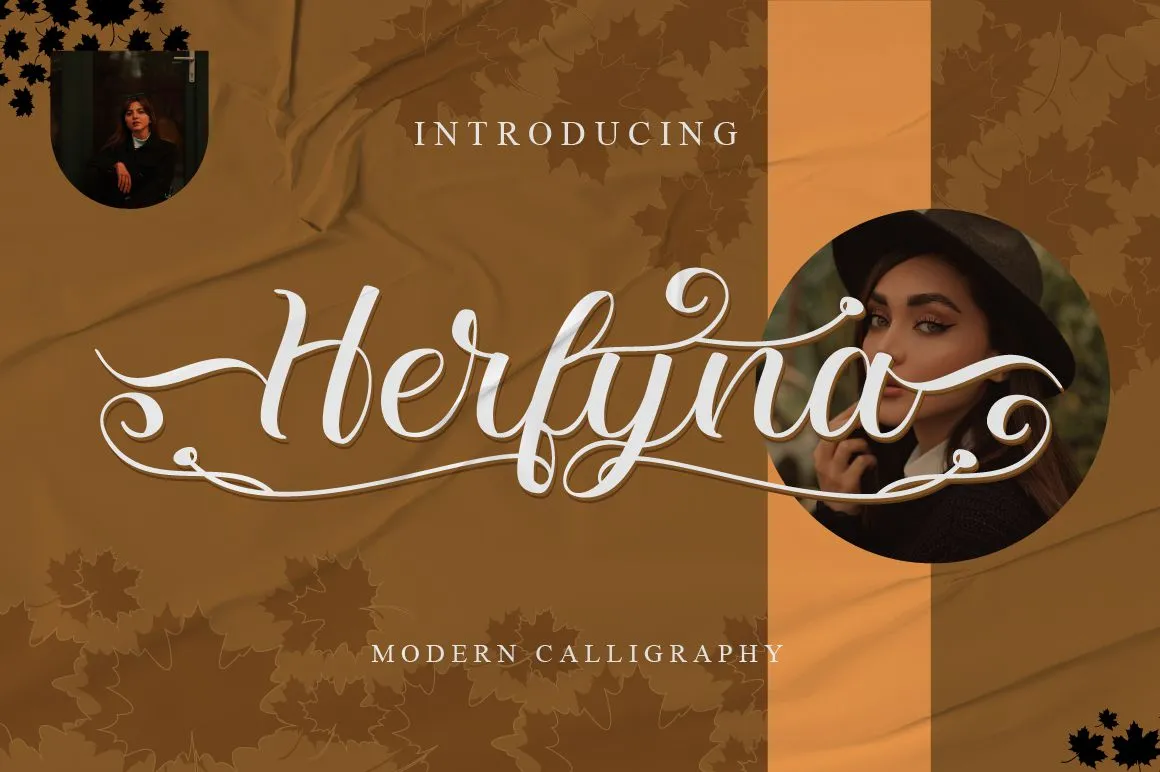
Herfyna Font – Fonte Grátis
Herfyna Font
A fonte “Herfyna Font” é uma elegante escolha para quem busca uma tipografia script refinada e sofisticada. Ela se destaca por seu estilo atraente, alternativas criativas e ligaturas meticulosamente feitas que garantem um acabamento perfeito em qualquer projeto. A fonte é PUA (Proprietary Unicode Association) encoded, tornando-a ainda mais versátil e prazerosa de usar. Ela oferece uma ampla gama de opções para criar designs memoráveis, com seus detalhes finos e harmoniosos que brilham em qualquer situação gráfica. Seja você um designer de sites, editor de revistas ou criativo em uma startup, a Herfyna Font é certamente um investimento valioso para seu arsenal de ferramentas de design.